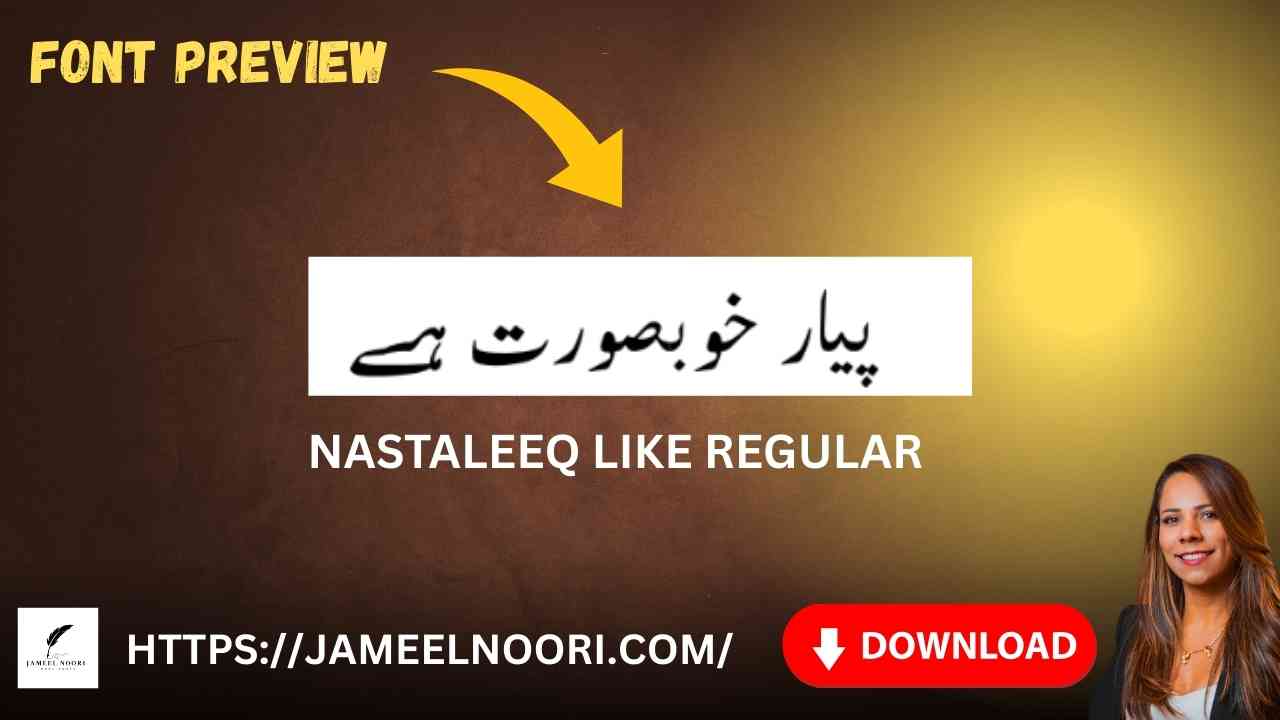
Download Urdu font Nastaleeq Like Regular Pakistan ke students, writers, aur designers ke liye ek essential tool ban chuka hai. Ye font apni smooth aur elegant calligraphy style ki wajah se Urdu documents, posters, aur digital projects me widely use hota hai. Agar aap professional ya personal purposes ke liye Nastaleeq Like Regular font download karna chahte hain, ye article aap ke liye step-by-step guide provide karega.
What is Download Urdu font Nastaleeq Like Regular?
Download Urdu font Nastaleeq Like Regular ek TrueType font hai jo Urdu text ko bilkul natural aur classic Nastaleeq style me represent karta hai. Is font ki khasiyat ye hai ke ye readable aur visually appealing hai, chahe aap printed documents bana rahe ho ya digital designs.
Ye font Urdu typing aur calligraphy projects ke liye sab se zyada recommended hai.
Features of Download Urdu font Nastaleeq Like Regular
Download Urdu font Nastaleeq Like Regular ki kuch important features ye hain:
- Elegant Nastaleeq Style: Classic Urdu calligraphy style ke saath modern readability.
- User-Friendly: Typing aur designing me simple aur smooth interface.
- Unicode Support: Har Urdu character aur special symbols ka proper display.
Uses of Download Urdu font Nastaleeq Like Regular in Pakistan
Download Urdu font Nastaleeq Like Regular ka use Pakistan me students aur professionals ke liye kaafi common hai. Kuch popular uses:
- Urdu assignments aur projects ke liye
- Magazines aur newspapers me calligraphy
- Graphic designing aur social media posts
- Digital invitations aur greeting cards
- Personal documents aur letters
Tips for Best Results with Download Urdu font Nastaleeq Like Regular